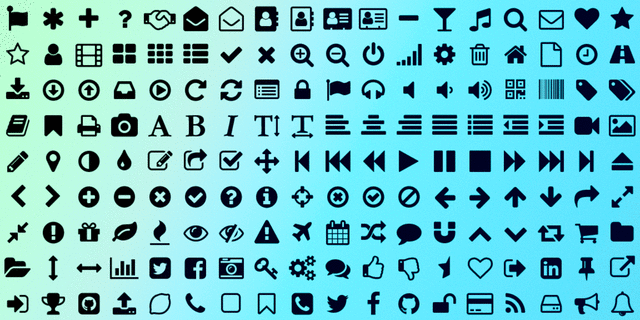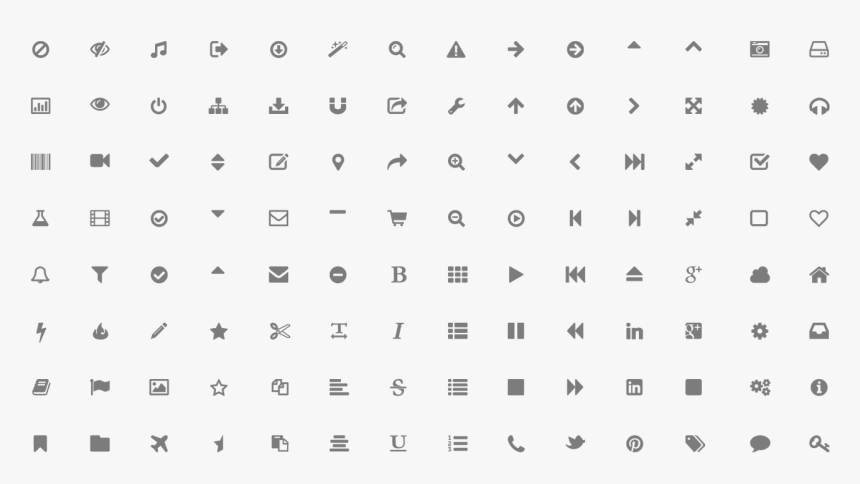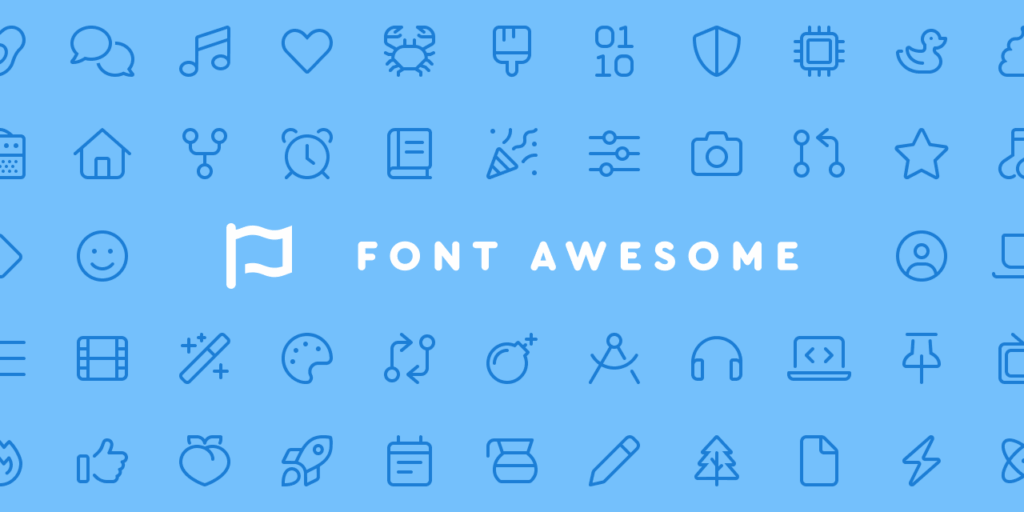
Font Awesome là bộ công cụ cung cấp hàng ngàn biểu tượng dưới dạng phông chữ hoặc tệp vector, giúp việc minh họa thông tin trở nên sinh động và hiện đại hơn. Trong lĩnh vực kiến trúc và xây dựng, việc download font Awesome giúp các nhà thiết kế dễ dàng đưa các icon mô tả thiết bị, sơ đồ vị trí hay các ký hiệu kỹ thuật vào bản vẽ và hồ sơ dự án một cách chuyên nghiệp.
Đặc điểm nổi bật của thư viện biểu tượng Font Awesome trong trình bày dữ liệu
Điểm thu hút của Font Awesome chính là tính linh hoạt vượt trội khi các biểu tượng được xử lý như một loại phông chữ thông thường. Điều này cho phép bạn thay đổi kích thước, màu sắc và hiệu ứng của icon mà không làm giảm chất lượng hình ảnh, kể cả khi phóng to trên các bảng hiệu công trường khổ lớn. Việc tải font Awesome giúp tối giản quy trình thiết kế, thay vì phải tìm kiếm từng tệp hình ảnh rời rạc, bạn chỉ cần gõ phím hoặc sao chép mã biểu tượng để hiển thị ngay lập tức.
Sự ổn định của hệ thống biểu tượng này còn nằm ở khả năng tương thích cao với nhiều môi trường khác nhau. Từ việc tích hợp vào giao diện website giới thiệu nhà lắp ghép đến việc sử dụng trong các phần mềm thiết kế chuyên dụng như Photoshop hay AutoCAD, Font Awesome luôn giữ được độ sắc nét. Đây là phương án hiệu quả để tạo ra các bản thuyết minh dự án khoa học, giúp khách hàng dễ dàng nhận diện các khu vực công năng thông qua hệ thống ký hiệu trực quan.
03 Ứng dụng bộ biểu tượng Font Awesome vào thực tế ngành xây dựng
Nhờ tính trực quan và hiện đại, việc sử dụng các biểu tượng từ thư viện Font Awesome mang lại giá trị thực tế cao trong quá trình triển khai dự án:
- Hệ thống ký hiệu trên bản vẽ mặt bằng: Sử dụng các icon trong gói download font Awesome 5 free solid để mô tả vị trí đèn, ổ cắm, thiết bị vệ sinh hoặc hướng di chuyển trong nhà lắp ghép giúp bản vẽ trở nên dễ hiểu hơn với khách hàng không am hiểu chuyên môn kỹ thuật.
- Thiết kế biển chỉ dẫn cho Homestay & Văn phòng: Việc download font Awesome 5 brands cung cấp các biểu tượng mạng xã hội và tiện ích giúp việc làm biển hiệu nội khu trở nên đồng bộ và thẩm mỹ hơn, tạo dấu ấn hiện đại cho không gian sống.
- Trình bày báo cáo và website giới thiệu dự án: Sử dụng các biểu tượng vector giúp các mục báo cáo tiến độ thi công hay tính năng vật liệu panel cách nhiệt trở nên tách bạch, chuyên nghiệp và thu hút sự chú ý của người xem.
03 Lưu ý sử dụng Font Awesome để tối ưu hóa hiệu quả thị giác
Để khai thác hiệu quả vẻ đẹp của kho biểu tượng đa năng này, người thiết kế nên lưu tâm một số lưu ý kỹ thuật sau:
- Duy trì tính đồng bộ về phong cách: Khi trình bày hồ sơ dự án, bạn không nên trộn lẫn giữa biểu tượng nét mảnh (Light) và nét đậm (Solid). Hãy chọn một phong cách xuyên suốt từ thư viện download font Awesome 6 pro để tạo nên sự thống nhất cho bản thiết kế.
- Kiểm soát kích thước và khoảng hở: Các biểu tượng nên có kích thước tương đồng với cỡ chữ đi kèm. Việc nới rộng khoảng cách xung quanh icon sẽ giúp bố cục thông tin trở nên thông thoáng, tránh cảm giác chật chội trên các bảng thông số kỹ thuật.